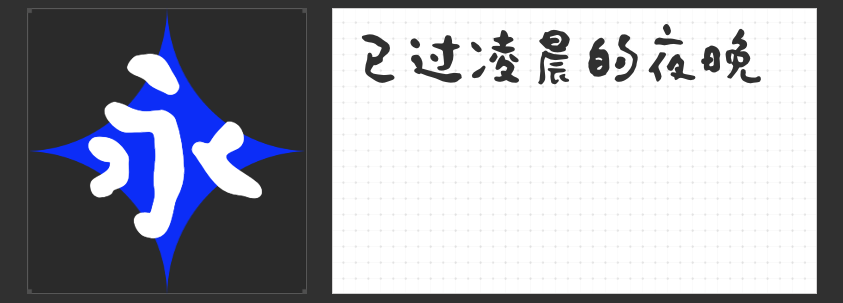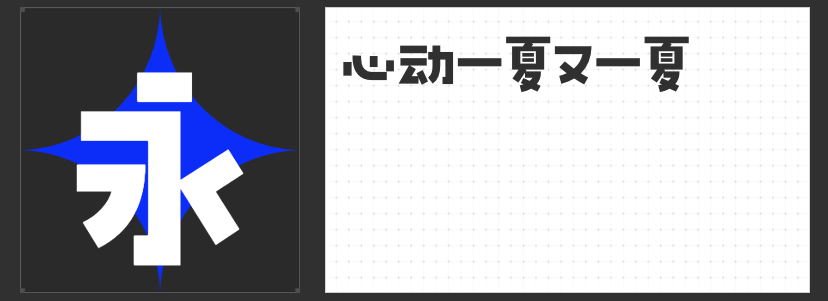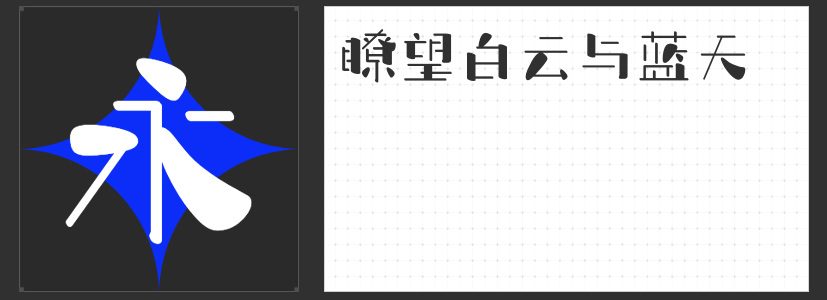
破次元壁的字体魔法🪄四款二次元魂字体点燃设计灵感
在二次元的世界里,文字不仅是信息载体,更是场景氛围的制造者。当凌乱的线条、扭曲的结构与手绘的温度相遇,字体便拥有了撕裂现实、重构幻想的力量。以下四款专为二次元创作而生的创意字体,以打破常规的骨骼设计和视觉张力,为漫画、游戏、同人创作注入灵魂燃料。
一、字恋狂白日梦简
这款字体如同被梦境泡影浸染的墨迹,线条在虚实间游移不定。锯齿状边缘与突然断裂的笔画,模仿着意识流绘本中碎片化的叙事节奏。适用于营造超现实场景、梦境回忆或魔法世界的文字特效,其不规则的轮廓自带“画面抖动”的视觉错觉,与赛博朋克或奇幻题材天然适配。
二、字恋狂石头简
将立体主义解构为平面狂欢,细如发丝的几何框架与饱满的圆形笔触碰撞出荒诞喜剧感。笔画末端刻意保留的“未闭合缺口”与结构错位,仿佛字体在生长过程中发生了基因突变。适合制作搞怪标语、游戏道具图标或漫画音效字,其“未完成感”恰是二次元文化推崇的“瑕疵美学”。
三、字恋狂深夜简繁
笔触如墨滴坠入宣纸般自然晕染,字形被水波纹揉皱成有机形态。繁体与简体字的混排设计,暗合二次元创作中时空交叠的叙事逻辑。适用于古风奇幻场景、液体特效标题或情感类漫画对白,其流淌的线条自带“被泪水浸泡”的叙事张力。
四、字恋狂澄空鸣风
在严谨与自由间走钢丝的美学实验——上松下紧的结构如气球漂浮,字面大小随字形舒展收缩,形成舞蹈般的节奏感。平直切角与断开式笔画设计,既保留手写温度又避免黏腻。适用于轻小说封面、角色台词气泡或动态海报,其灵活骨架能完美融入各种“萌系”或“燃系”场景。
这四款字体打破了传统字库的“背景工具”定位,以夸张的表演欲成为场景中的戏剧角色。它们或癫狂或慵懒的视觉语言,与二次元创作中追求“瞬间冲击力”的核心诉求不谋而合。更重要的是,其免费商用的属性(请遵循具体授权条款)让独立创作者也能放肆玩梗。下次设计角色台词气泡时,不妨让它们替你讲述一个更狂野的故事。